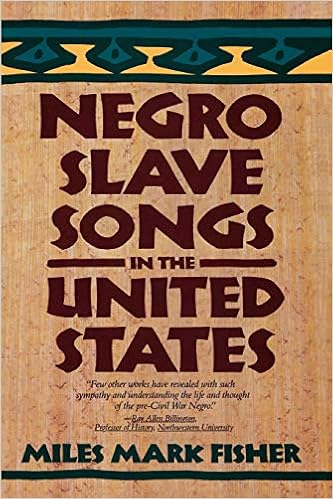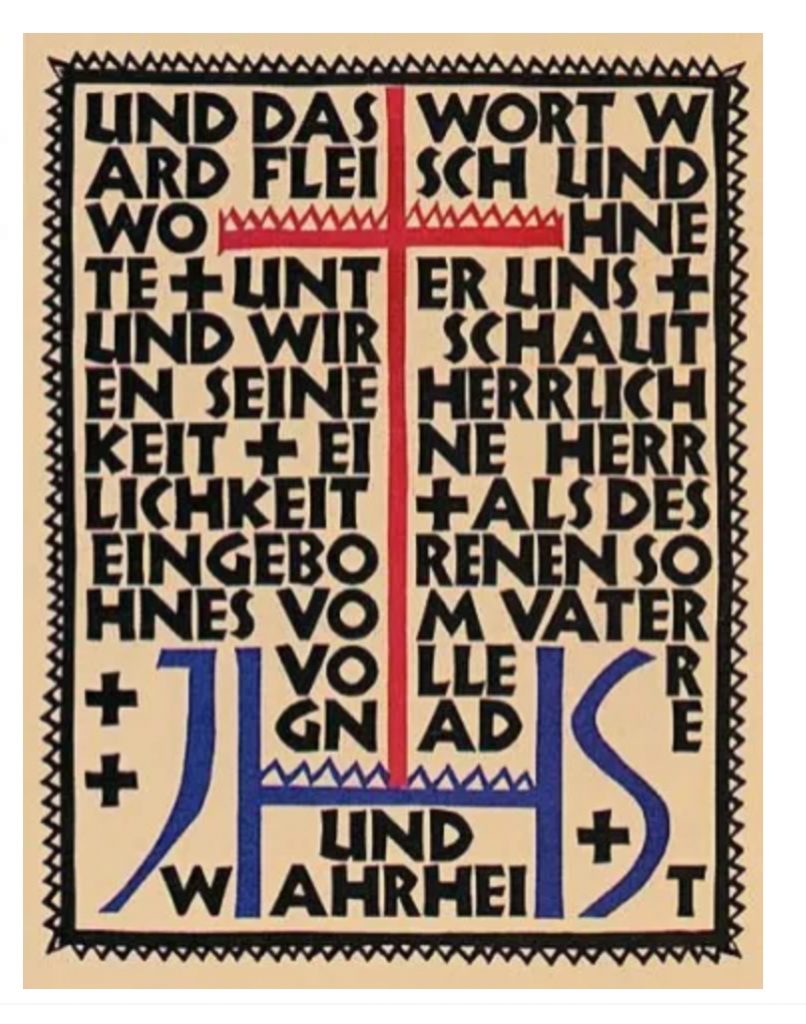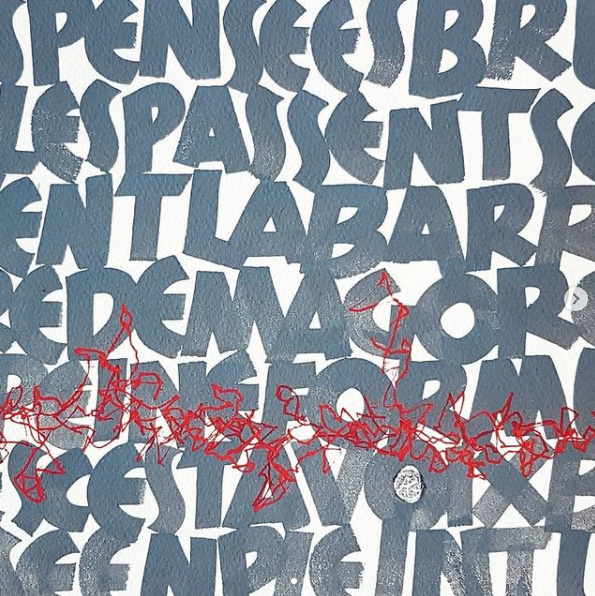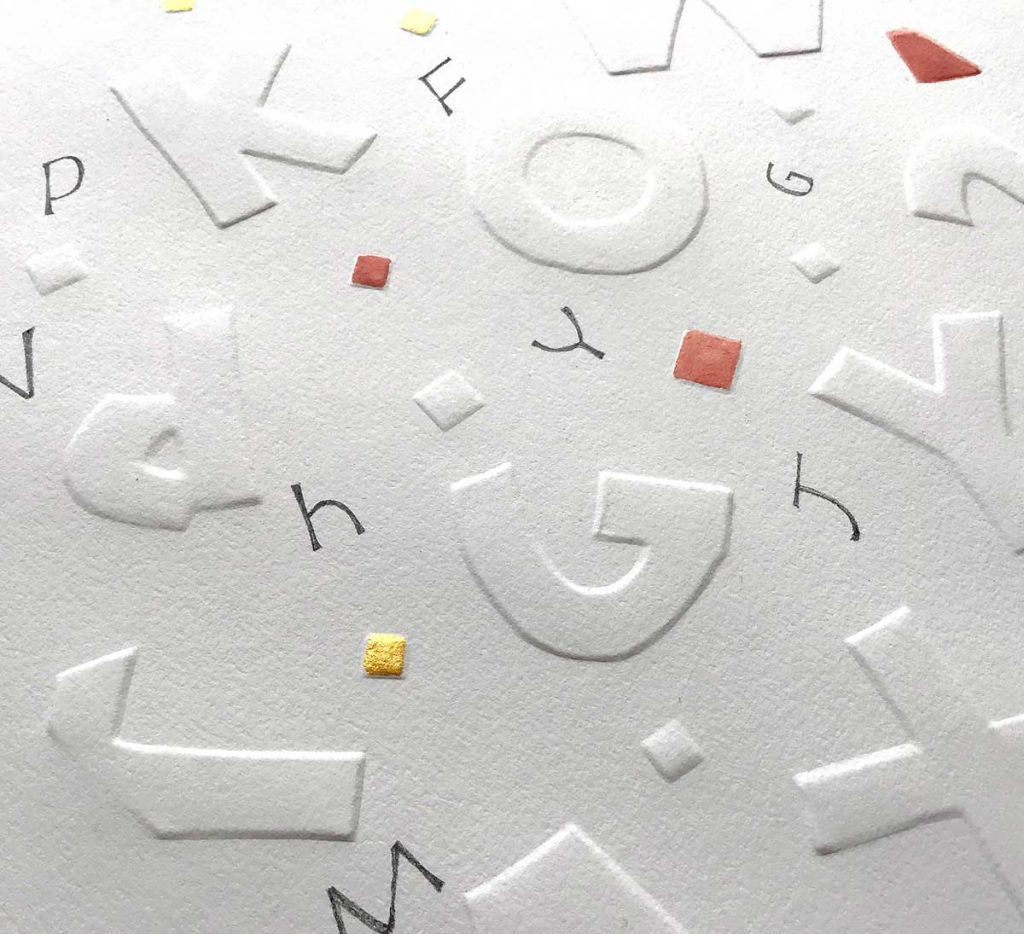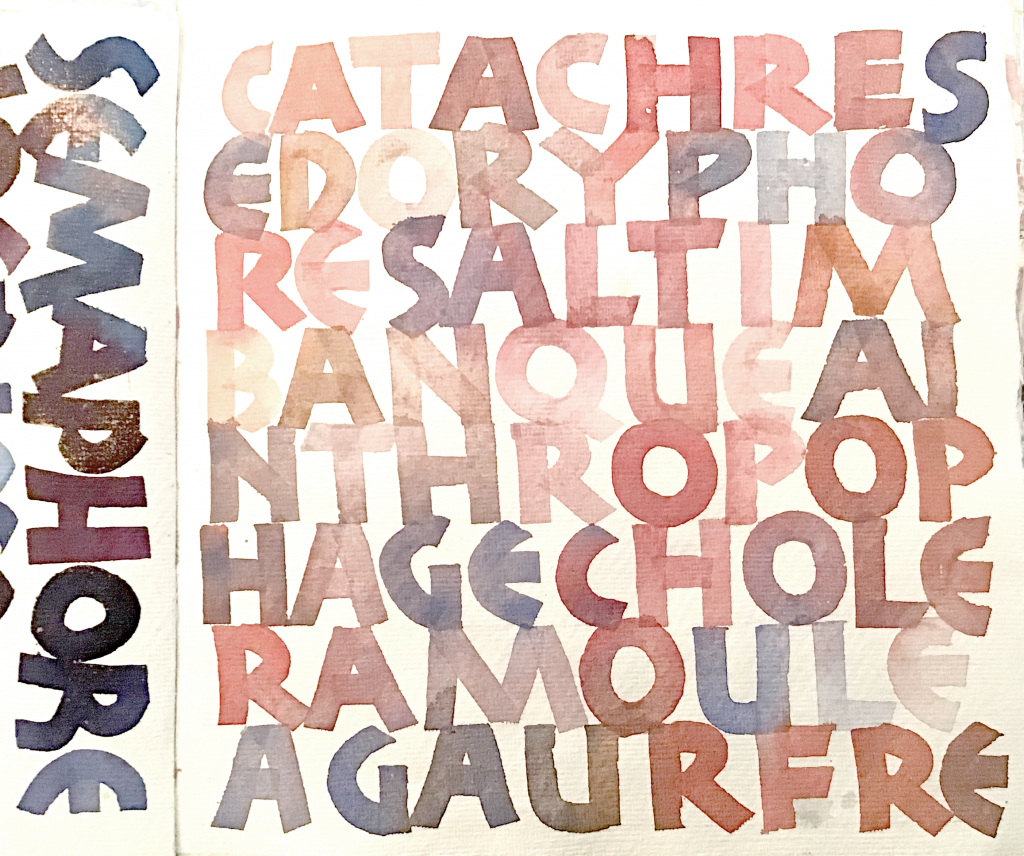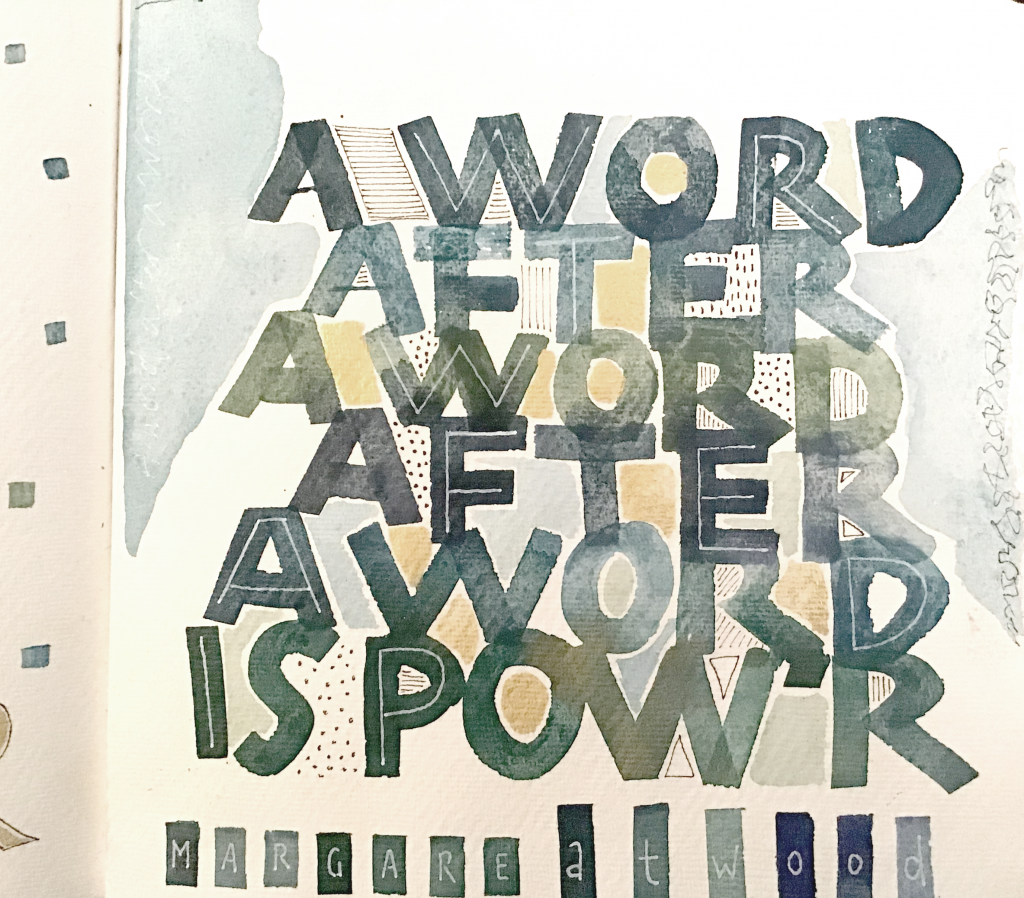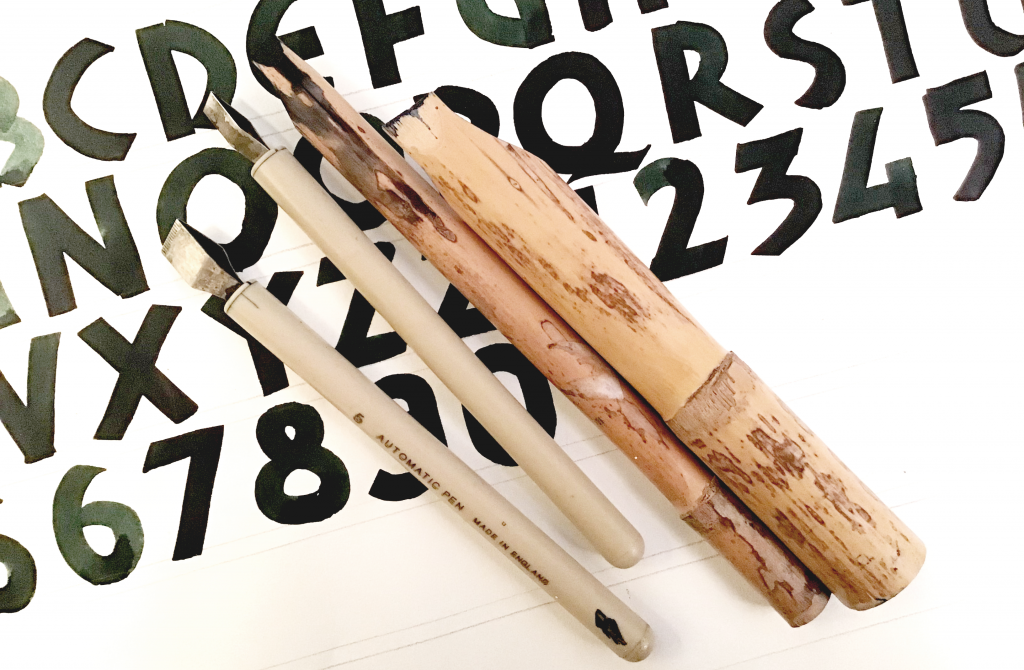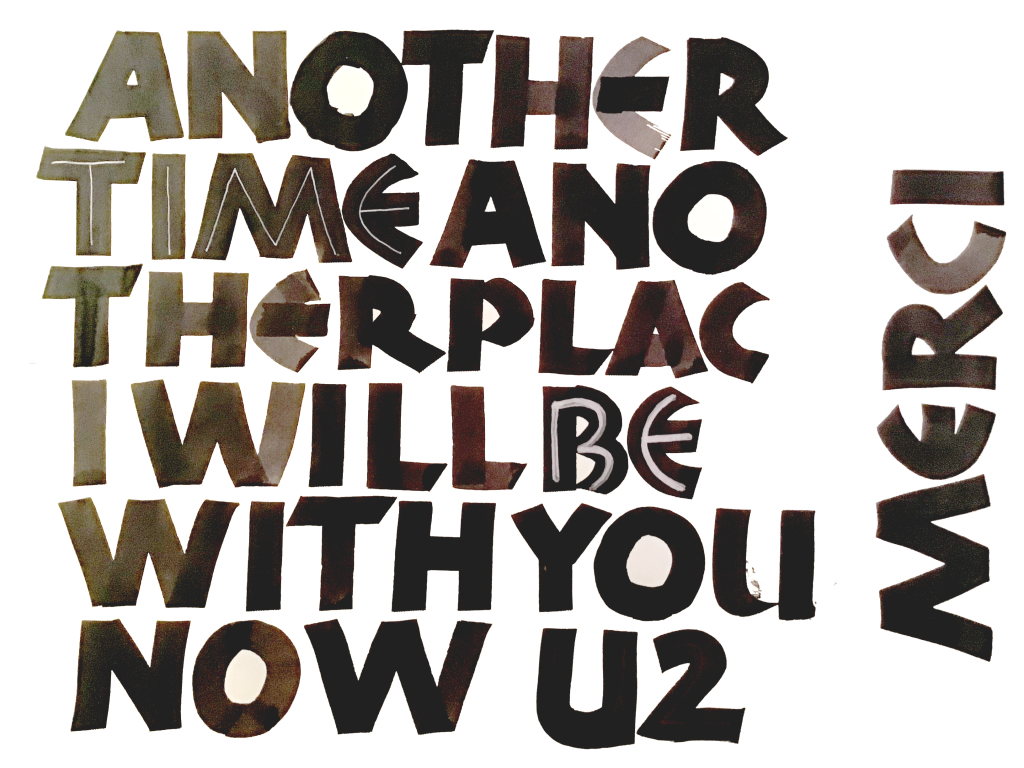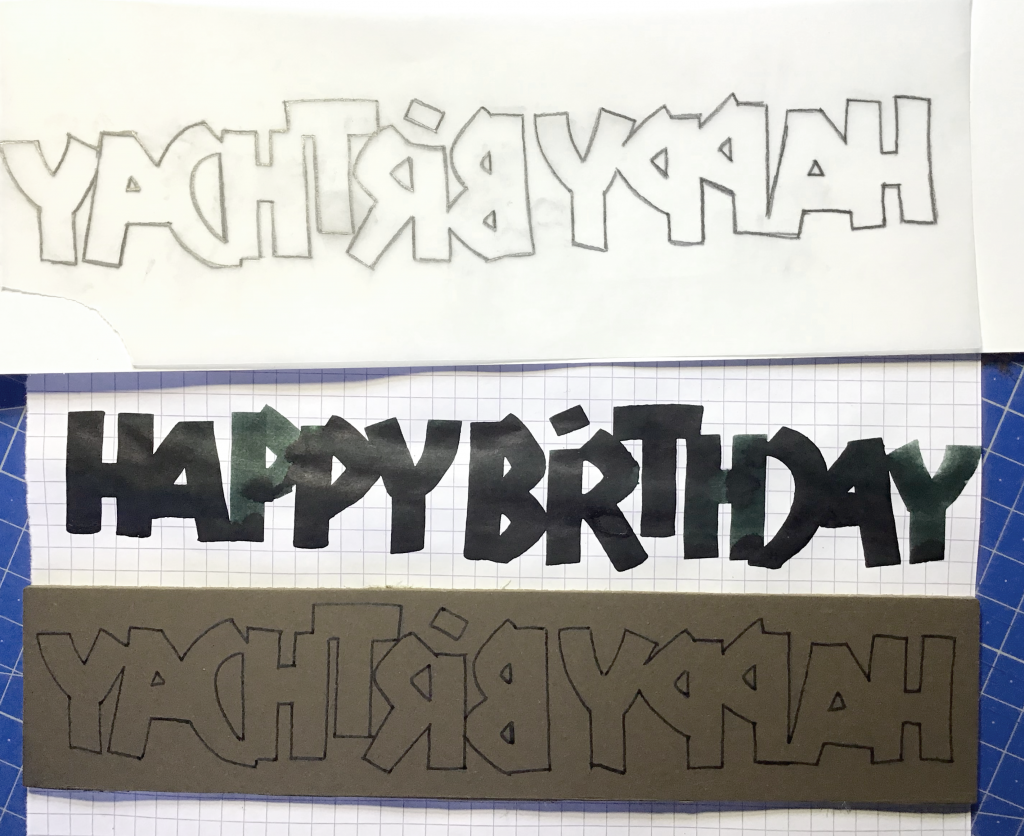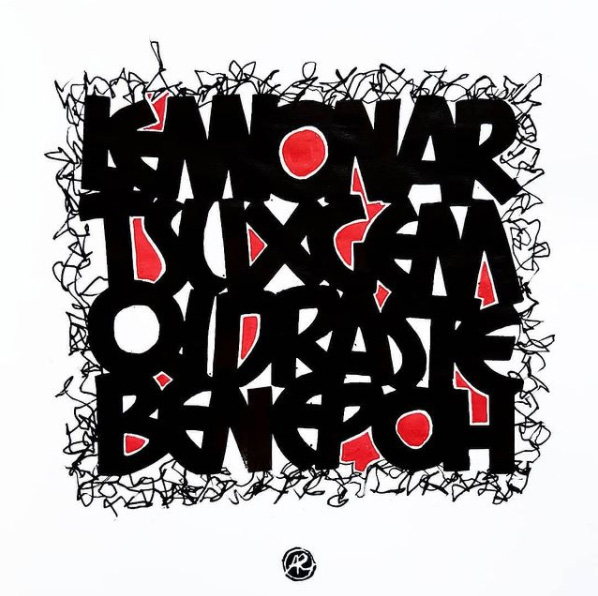
Plongée dans les capitales libres depuis quelques mois, je me suis repenchée sur la Neuland que j’avais un peu pratiquée il y a quelques années. Initialement, la Neuland est une typographie et non une écriture, mais elle est couramment utilisée en calligraphie moderne, sans doute car on apprécie son aspect très graphique.
Edit 11/04/21 : on me souffle dans l’oreillette qu’il y avait bien une écriture avant la typo, et que celle-ci est décrite dans le livre de Koch “Das Schreibüchlein”. Si quelqu’un a une planche à partager, je suis preneuse !
Afin de mettre un peu de contexte – ce que j’aime toujours faire ! – je vous propose une petite genèse de cette écriture typographie et quelques exemples appliqués à la calligraphie. C’est parti !
A l’origine, des caractères gras, imposants et lisibles de loin
C’est le typographe allemand Rudolf Koch qui a mis au point la Neuland en 1923. Il cherchait un caractère imposant et lisible de loin qui se démarquerait des traditionnelles gothiques alors très répandues dans les titrages et la publicité en Allemagne. En outre, il souhaitait un caractère sans empattements, avec une sorte de force brute, mais toutefois humanisée : il se mit donc à l’ouvrage et grava directement ses caractères dans des plaques de métal, sans dessins préalables.
Cette démarche produisit le résultat attendu – à savoir une typo grasse et imposante – avec toutefois de subtiles variations de taille d’une lettre à l’autre, un certain cintrage, qui lui apportait finalement cette touche humaine et non “industrielle”.
On remarque en effet que les lettres ne sont pas totalement rectilignes, et que la graisse des lettres bien que constante n’est pas écrasante car elle est légèrement pincée/cintrée (je le dis avec mes mots à moi, si un typographe passe par ici qu’il ne me tire pas dessus tout de suite, merci !).
A l’époque, les production publicitaires allemandes utilisent malgré tout beaucoup la gothique, ainsi que des caractères Art Nouveau plus élégants, fins et élaborés. Finalement, la Neuland ne trouve pas tellement sa place en Europe.
Un caractère manquant de noblesse et d’élégance, qualifié de “caractère poubelle“
Vendue à des imprimeurs américains comme une nouvelle typographie publicitaire, la Neuland connu un succès plus que mitigé également Outre-Atlantique et son usage emprunta une voie non prévue par son créateur Rudolf Koch. Jugée inélégante, trop brute, manquant de noblesse, cette typographie qualifiée de “caractère poubelle” fut rapidement utilisée pour des productions fonctionnelles (tracts, affiches, cartes) souvent destinées au peuple afro-américain. Remettons-nous dans le contexte de l’époque : la culture afro-américaine est naissante et pleinement liée à l’esclavage, à la culture du tabac et du coton.
Bon an mal an, toujours à l’instar de son créateur Rudolph Koch, la Neuland devint finalement un marqueur de la culture afro-américaine, et par extension de l’exotisme, de l’africanisme, de la culture tribale et primitive.
Ses formes simples et brutes, issues de la capitale romaine primitive, évoquent en effet cet aspect très… primitif. Utilisée dans ce contexte dans la publicité, sur les couvertures de livres, les pochettes de disques, les affiches de cinéma, la Neuland deviendra une “typo stéréotypée” – connotée raciste par certains et comme on dirait aujourd’hui “black face”. Sur une note moins politique, on notera l’usage de la Neuland comme marqueur d’aventure et d’exotisme dans les affiches de Jurassic Parc ou Jumanji.
Curieux destin que celui de cette typographie, surtout si je vous révèle maintenant que Rudolf Koch, très éprouvé par la Première Guerre mondiale, avait trouvé refuge dans la foi chrétienne : son intention initiale avec la Neuland (qui signifie Nouveau Monde en allemand) était de créer une police audacieuse et visible qui “crierait” aux autres Allemands que suivre le chemin de Dieu les aiderait à trouver du réconfort suite au traumatisme de la grande guerre. Une intention bien loin de l’interprétation et de l’usage qui ont été faits de sa création !
L’utilisation de la Neuland en calligraphie
Si vous parcourez mon tableau “calligraphie moderne” dans Pinterest, vous verrez de nombreux usages de la Neuland par les calligraphes. Bien que ce ne soit pas une écriture, mais une typographie, elle est intéressante justement à cause de son aspect très brut, imposant et définitivement moderne.
Les subtiles variations au niveau des hauteurs de lettres, du cintrage lui confèrent une dynamique toute… calligraphique, finalement !
Graphiquement, c’est un terrain de jeu inépuisable où l’on peut exploiter le contraste et les contreformes pour des compositions modernes et originales.
Les outils pour pratiquer la Neuland
Il faut des outils larges, pour bien exploiter cette forme généreuse : on laisse tomber les plumes pour le calame, l’automatic pen, le parallel pen ou le pinceau plat (un peu plus touchy, préférez un outil “dur” si vous débutez). Une bonne largeur de lettre se situe entre 5mm et 1cm. Après on peut voir encore plus large et tester avec de la cagette, pourquoi pas !